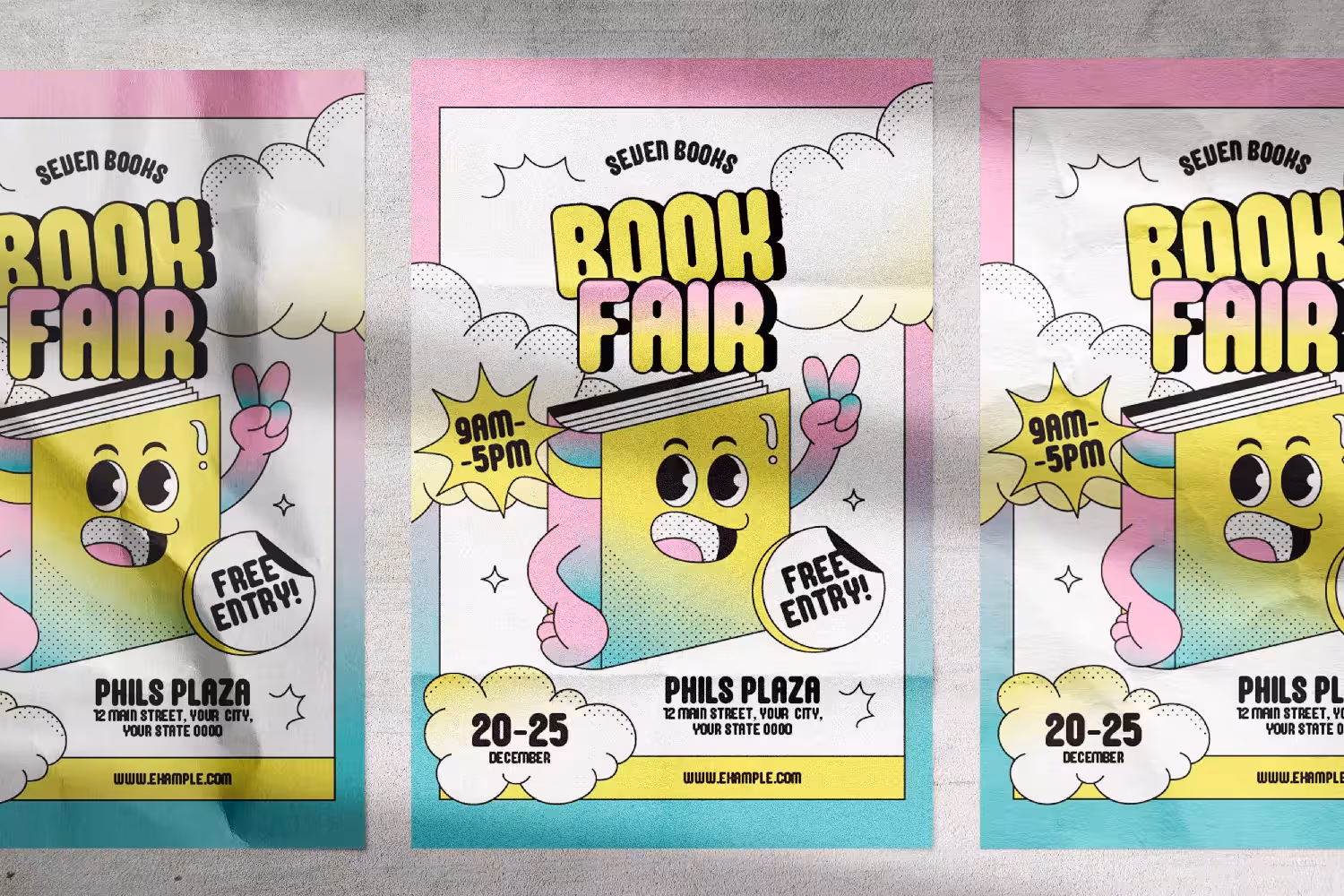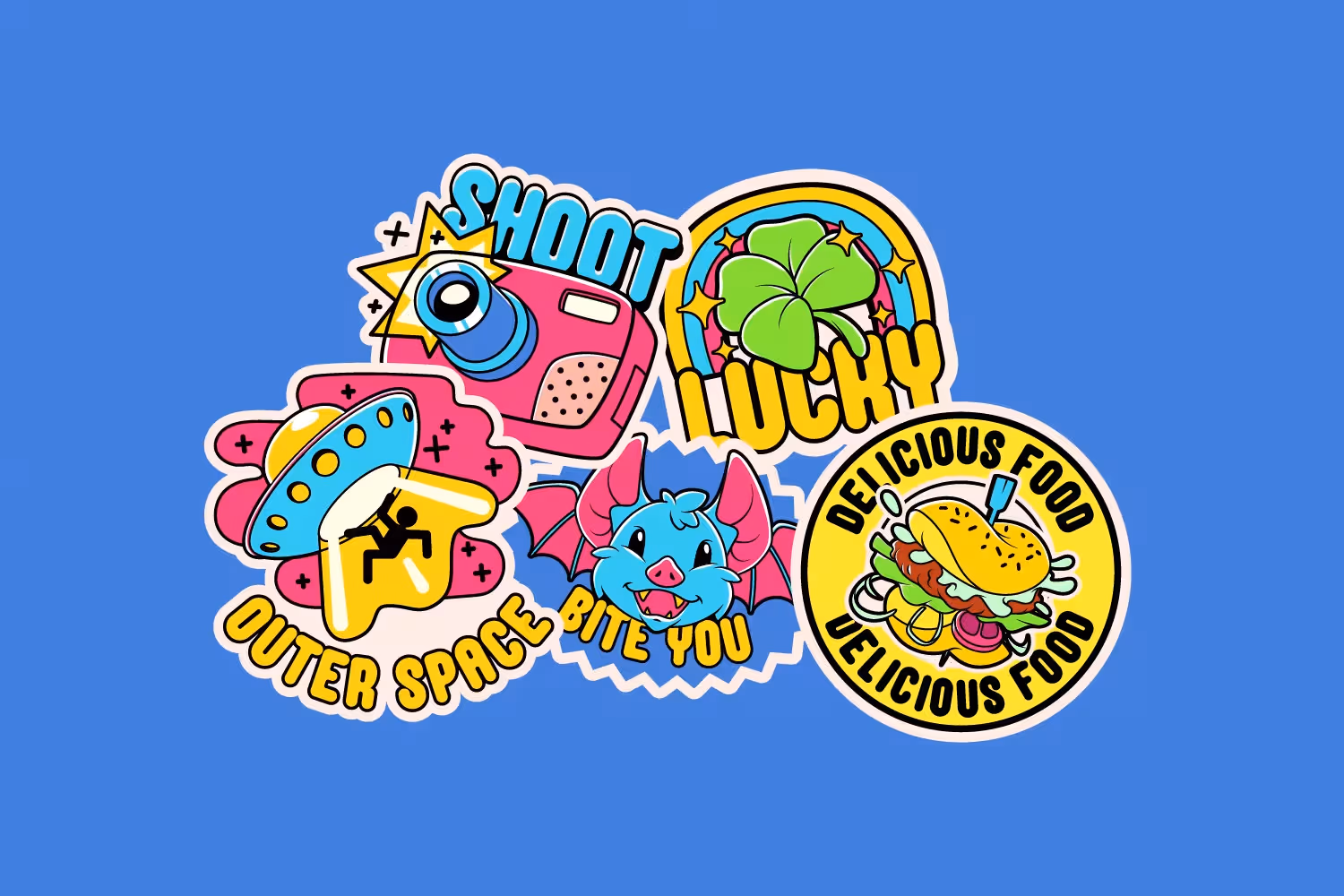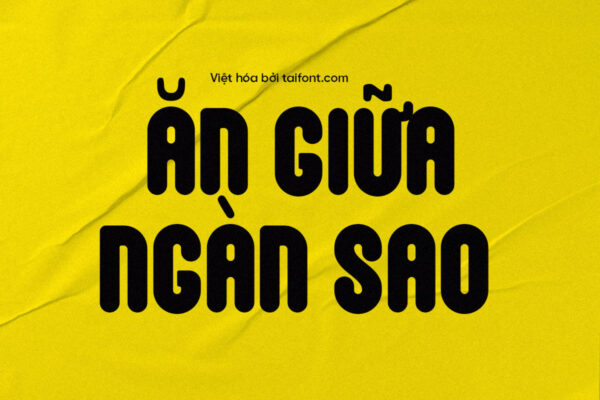
Giới thiệu về Font TF Monom Việt hóa
TF Monom Việt hóa là một font chữ không chân (sans-serif) với phong cách đứng, hiện đại và các nét được bo tròn mềm mại. Sự kết hợp này mang lại vẻ ngoài thân thiện, độc đáo nhưng vẫn rất rõ ràng và dễ đọc, tạo cảm giác vừa hiện đại vừa ấm áp.
Với đặc điểm nổi bật là nét đứng vững chắc và hình dáng mềm mại, TF Monom là lựa chọn lý tưởng cho các thiết kế cần sự thu hút và dễ chịu:
- Thiết kế ẩm thực: Hoàn hảo cho menu quán ăn, nhà hàng, bao bì sản phẩm thực phẩm, hoặc poster quảng cáo món ăn. Font này giúp gợi cảm giác ngon miệng, sự dễ thương và ấm cúng, làm cho các món ăn thêm phần hấp dẫn.
- Thiết kế banner: Lý tưởng cho các banner quảng cáo trực tuyến hoặc in ấn, giúp tiêu đề và thông điệp trở nên nổi bật, dễ đọc từ xa và thu hút sự chú ý.
- Thiết kế cho trẻ em: Phù hợp cho bao bì sản phẩm, sách truyện, hoặc các ấn phẩm hướng đến trẻ nhỏ, tạo không khí vui tươi và ngộ nghĩnh.
Với TF Monom Việt hóa, bạn có thể dễ dàng tạo ra những thiết kế không chỉ đẹp mắt mà còn rất hiệu quả trong việc truyền tải thông điệp một cách rõ ràng, thân thiện và đầy phong cách.